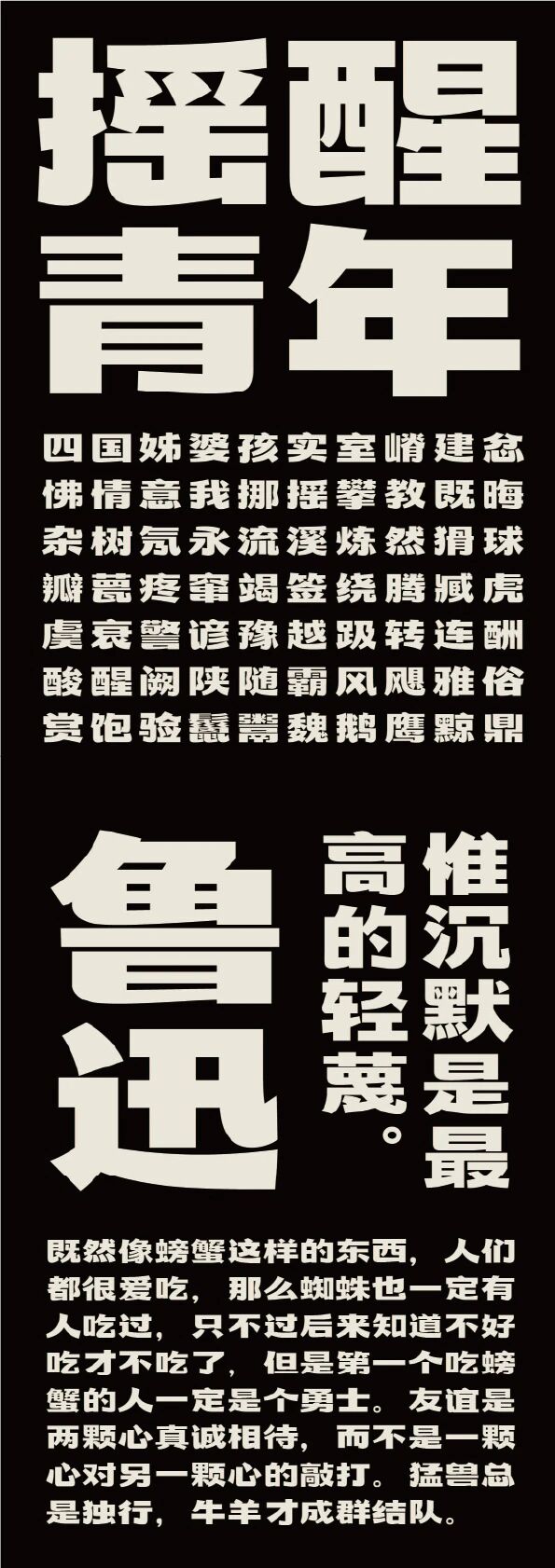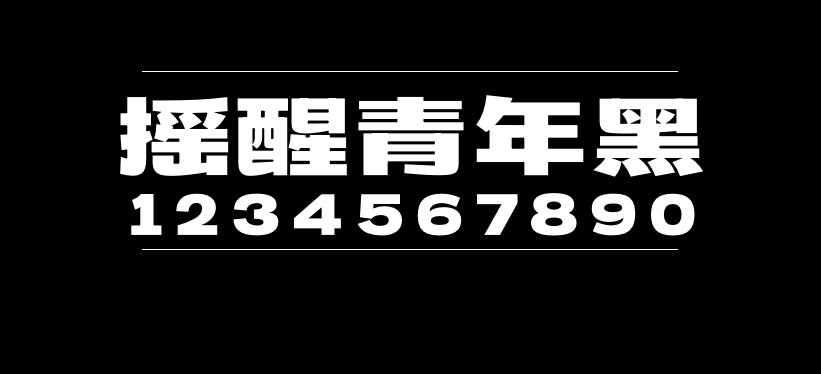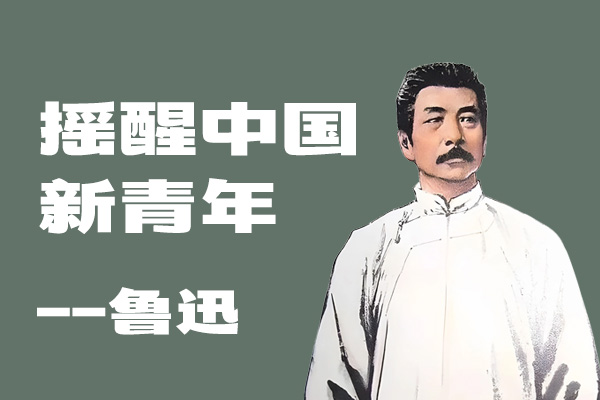
摇醒青年黑
摇醒青年黑 是一款由“摇醒实验室”发起的、充满青春活力的共创字体。经过6个月的努力,200+设计师的共同创造,这款字库终于面世,并惊喜地提供免费可商用授权。无论是用于海报标题,还是其他设计项目,摇醒青年黑都能让你眼前一亮,迸发出无限创意。
摇醒青年黑的灵感来源于1951年由北新书局出版的《美术字的写法和练习》中的第23到28页。它兼具黑体和宋体的笔画特征,整体偏向黑体,但撇画与点画更接近宋体,是一款创意十足的字体。快来体验这款融合了黑体和宋体元素的创意字体吧!